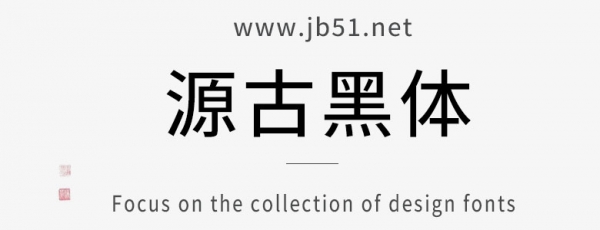
源古黑體是一款不錯的藝術字體,基于思源黑體改造,擴B區(qū)的字取自遍黑體,字體端正大氣,具有很好的視覺感,適合應用于藝術設計、平面宣傳設計、網頁設計,書法字帖等領域,需要的朋友可以前來本站下載。
在工具包做出發(fā)布了兩款古籍規(guī)范的字體源古黑體與源古宋體,黑體基于思源黑體改造,擴B區(qū)的字取自遍黑體。宋體基于思源宋體改造,擴B區(qū)的字取自文津宋體。
得益于思源豐富的地區(qū)字形,拆拆湊湊很方便就可以改出一個古籍表版本。而關于那些部件不統(tǒng)一的字,我有選擇性地擅自進行了統(tǒng)一。
然后黑體和宋體各提供了兩個版本,一個是僅包含古籍表表內字的純古籍表版,一個是把古籍表外的——思源本來有的那些字一股腦放進去的“F”版本(當然這些表外字就沒有按古籍表規(guī)范修改,保持思源原樣)。